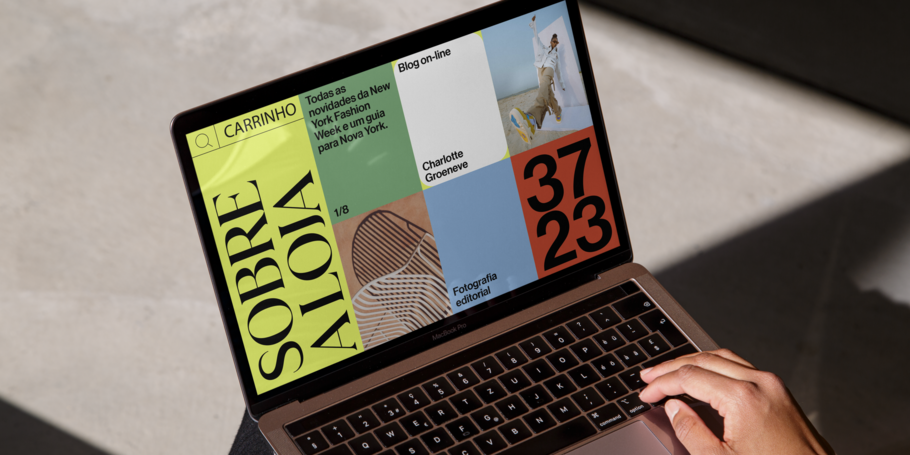
Como as expectativas de experiência do usuário mudaram e o que isso significa para o uso das fontes.
“ Os usuários de hoje se comportam de outra forma on-line e esperam mais das marcas. ”
Como as expectativas dos clientes mudaram e o que isso significa para você.
Caso você tenha se perdido aqui: tem havido algumas grandes mudanças no mundo e na cultura ultimamente! Com o risco de atribuir tudo que acontece na sala à COVID-19, a pandemia global provocou uma sensação duradoura de isolamento e uma confiança mais profunda nas experiências digitais.
A mudança climática também acelerou o interesse do consumidor em biodiversidade e sustentabilidade. Por fim, os movimentos de direitos civis e à atenção às marcas quanto às iniciativas de diversidade, equidade e inclusão e ao ativismo. Continue lendo para compreender como essas mudanças influenciam as expectativas do consumidor em torno do design, a experiência do usuário e as maneiras como elas se identificam com sua marca.
A pandemia mudou as expectativas digitais de todo mundo.
Entre lockdowns, “escola via Zoom” e grandes partes da população mudando para o home office, o tempo em casa e com telas aumentou muito nos últimos anos. Ficamos presos a dispositivos retangulares em todas as formas e tamanhos, e, para muitos, as interações com as telas se tornaram as únicas interações do dia. E para muitos, isso acelerou o costume de se comunicar com marcas digitalmente. Antes da pandemia, trocar mensagens com uma marca ficava em quinto lugar no uso de canais de atendimento ao cliente, agora é o segundo. Em reação, as marcas mais inteligentes mudaram da postura fria, rígida para dar informações para encontrar maneiras de se identificar, empatizar e buscar a solidariedade com seus cliente.
O efeito dominó do design foi esse: as empresas encontraram maneiras de simpatizar com as lutas diárias do mundo por meio de uma troca de mensagem mais gentil e um design mais suave. Pela primeira vez, “consumidores regulares do dia a dia” fora da comunidade do design começaram a reconhecer que as informações que vemos em espaços digitais com frequência são criadas com os mesmos modelos, as mesmas fórmulas, as mesmas fontes. Os gerentes de marca e criativos perceberam a falta de variedade, a falta de distinção e humanidade no formato de nossos artigos digitais.
A pandemia obrigou as marcas a lançarem mais aplicativos e novos serviços.
Antes da pandemia, muitas marcas não tinham uma experiência digital abrangente porque a “experiência”, tal como era, ficava relegada ao olhar e tocar. A maravilha do digital é o nível de interação, o jeito que movemos o mouse, reagimos a menus, animações e respondemos a perguntas. Levando tudo isso em conta, as marcas começaram a fazer sua voz mais adaptativa e mais individualizada do que jamais tinham feito antes. Um exemplo principal disso em design é a implementação de fontes variáveis e como elas podem se adaptar a todos os tipos de cenários.
Talvez haja argumento sobre se trabalhar de casa leva a mais produtividade, mas retirar os trajetos para ir ao trabalho e o tempo no trabalho fez com que muitas pessoas ficassem hiper-eficientes e, por sua vez, aumentou suas expectativas por respostas e experiências rápidas ou mesmo instantâneas. As pessoas almejam assumir mais riscos no espírito da rapidez: receber coisas em casa em vez de comprá-las em lojas, mesmo se isso significar perder perspectivas de segurança das informações financeiras pessoais. Por sua vez, as empresas tiveram que se esforçar para oferecer personalização, privacidade e medidas de segurança. Embora a fonte variável não tenha atingido sua maturidade, as fontes variáveis possibilitam às marcas a chance de falar em muitas vozes, fornecer experiências de usuário mais direcionada e “perfis de personalidade”, por assim dizer.
A catástrofe da pandemia levou a um desejo coletivo por entretenimento e fuga.
No espaço de mais ou menos dois anos, saltamos das compras on-line para caminhar em lojas virtuais e experimentar roupas que são visualizadas em pixels. A sensação de ansiedade, o isolamento e o tempo maior em casa aceleraram o conforto do consumidor com novas tecnologias e experiências virtuais. Precisa de prova? Basta olhar o metaverso, uma área que teve uma quantidade gigantesca de investimento e exploração criativa. As fronteiras entre “real” e “virtual” estão se expandindo, e se espera que as marcas projetem as experiências que entregam nesses espaços:
Fatores múltiplos estão levando a uma explosão no ativismo de marca.
Vamos voltar à realidade. Conforme mencionado antes, estamos todos um pouco mais conscientes de causas como sustentabilidade, diversidade, equidade e inclusão; e, por sua vez, o ativismo das marcas está bombando. Não é novidade que as pessoas se importam mais do que costumavam fazer, mas o que é notável é que os consumidores são mais influenciados pelo ativismo de marca do que com o propósito de marca. Os clientes procuram afinidade com marcas que buscam justiça em nosso mundo, e isso vai além da missão de uma marca. As pessoas querem ver marcas ativamente envolvidas em resolver problemas sociais.
Indo alguns níveis mais a fundo, os consumidores se importam com o que uma marca inerentemente representa: segundo quais princípios orientadores elas vivem, e os princípios da marca são definidos de cima para baixo. Os princípios orientadores não são apenas “ideais”, os consumidores podem enxergar através disso. Eles precisam de valores genuínos e fortalecedores da vida que são sentidos em todos os pontos de contato da marca. Um exemplo da vida real do Diretor Executivo de Criação da Monotype, Phil Garnham: “Somente nesta manhã eu fiz a assinatura de um novo produto de lavanderia sustentável devido ao desperdício de plástico em excesso criado pelas maiores marcas dos supermercados”, compartilhou Garnham. “Eles anunciaram nas redes sociais. Não foi a estética visual do anúncio que me atraiu – foi o fato de que eu podia fazer melhor, economizar dinheiro, era digitalmente eficiente e tinha um elemento de ‘bondade cosmopolita’, por assim dizer”. O conteúdo nativo em um espaço que ele já frequentava (Instagram), combinado com a conveniência da experiência digital e a capacidade de fazer o “bem cosmopolita” foi suficiente para levar Garnham a clicar em “Assinar”. Um caso de uso da vida real mostrando por que se deixar impulsionar pela missão importa.
Então, como as tendências e as expectativas do consumidor se relacionam?
Não se limita às perspectivas deles em como partem o cabelo e estilos de jeans, o tom e as expectativas da Geração Z estão deixando difusas todas as populações. Chegando à maior idade em um momento turbulento, essa geração é, sem dúvida, a primeira a exigir mais das empresas com que se alinham e das quais compram. O que estamos vendo é um efeito dominó de consumidores conscienciosos que causam uma mudança ampla na liderança corporativa.
Dito isso, não há parâmetro, o parâmetro é definido pelo mercado em que você opera e também pelas marcas que existem no mercado. Como gerente de criatividade e marca, o único marco que você devia medir é a criação das experiências de design mais engajadoras e inovadoras que você pode oferecer aos seus clientes. Se puder criar alguma coisa nova, ou pôr um toque diferente em algo que faça com que ela pareça nova e única, a marca se destacará. Melhorando isso, inclua uma camada extra de significado com a narrativa criativa e as mensagens personalizadas que atendam aos seus clientes. Aí é quando você sabe que acertou no seu brief criativo e alcançou suas expectativas (ou a de seus clientes) ao fazer a história da marca brilhar.